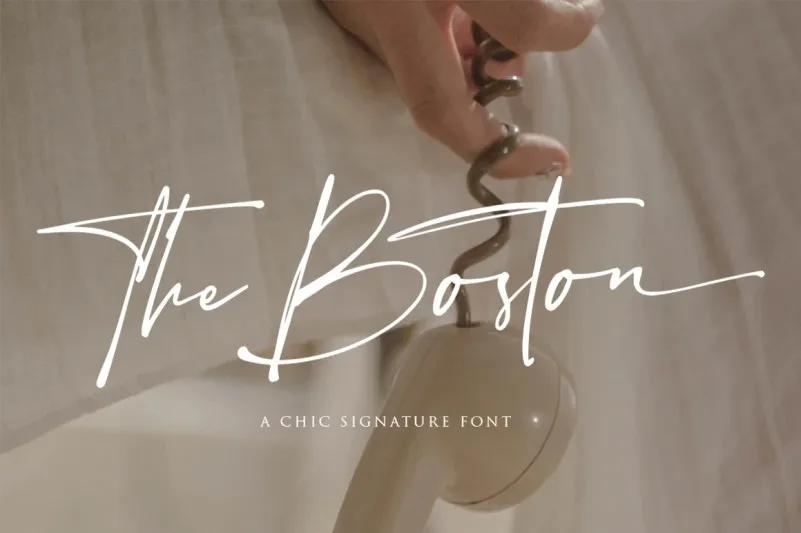
The Boston Font – Download Grátis
A fonte “The Boston Font” é uma elegante escolha para aqueles que buscam um touch moderno e artesanal em suas criações digitais. Inspirada nas escritas manuscritas de amor contemporâneo, esta fonte moderna tem traços casualmente variados, oferecendo um toque peculiar que se tornará o centro das atenções em qualquer projeto gráfico. Com ligaturas e estilos alternativos prontos para uso, “The Boston Font” adicionará uma visão única e vivaz ao seu design, garantindo que sua arte seja notada e marcante nas mãos de qualquer designer. Ideal tanto para aplicativos como para criações digitais, essa fonte oferece um estilo distintivo que certamente fará a diferença em seus projetos.